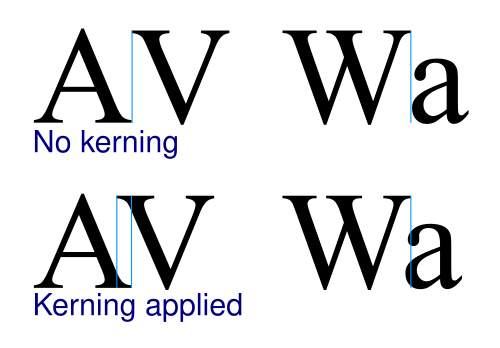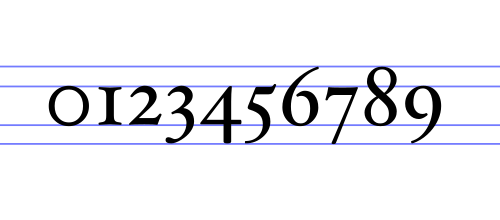
金属 活字組版において、フォント(アメリカ英語) またはファウント(イギリス英語) とは、書体の特定のサイズ、太さ、スタイルであり、全体的なデザインを共有するフォントのセットとして定義されます。たとえば、Bauer Bodoni書体 (図を参照) には、「 Roman」(または「regular」)、「bold」、および「italic 」のフォントが含まれており、それぞれさまざまなサイズがあります。
フォントのデジタル記述(コンピュータフォント)では、「フォント」と「書体」という用語はしばしば同じ意味で使用されます。[1]たとえば、コンピュータで使用する場合、各スタイルは個別のデジタルフォントファイルに保存されます。
従来のタイプセッティングとコンピューターの両方において、「フォント」という言葉は書体の配信メカニズムを指します。従来のタイプセッティングでは、フォントは金属または木製の活字から作られ、ページを構成するには複数のフォント、さらには複数の書体が必要になる場合があります。
綴りと語源
フォント(米国)またはファウント(英国では伝統的、いずれの場合も/ f ɒ n t /と発音)という単語は、中世フランス語の「鋳鉄」を意味する fonte に由来しています。[ 2 ]この用語は、活字鋳造所で金属活字を鋳造する工程を指します。綴りのfont は主に米国で使用されていますが、fount は歴史的にほとんどの英連邦諸国 で使用されていました。
金属タイプ
手作業による印刷 (活版印刷) 工場では、「フォント」という言葉は、ページ全体を植字するために使用される金属活字一式を指します。大文字と小文字は、手作業による植字の際に金属活字がどちらのケースに配置されていたかによってその名前が付けられます。つまり、大文字はより遠く、小文字はより近いということです。同じ区別は、大文字と小文字という用語でも表されます。
デジタル書体とは異なり、金属フォントには各文字の単一の定義は含まれませんが、よく使用される文字 (母音やピリオドなど) には、より多くの物理的なタイプピースが含まれます。新品で購入したフォントは、多くの場合 (たとえばローマ字の場合) 12pt 14A 34a として販売されており、これは、14 個の大文字の「A」と 34 個の小文字の「a」を含む 12ポイントフォントであることを意味します。
残りの文字は、その言語の文字の配分に適した量で提供される。ダッシュ、スペース、行の高さのスペーサーなど、植字に必要な金属活字の一部は、特定のフォントの一部ではなく、どのフォントでも使用できる汎用的な部分であった。[3]行間隔は、行間隔に使用されるストリップが鉛(他の部分に使用されているより硬い合金ではなく)で作られているため、今でも「リーディング」と呼ばれることが多い。このスペーシングストリップが鉛で作られているのは、鉛が従来の鍛造金属活字片(鉛、アンチモン、スズの一部)よりも柔らかい金属であり、印刷「チェイス」(つまり、すべての活字を一緒に保持するキャリア)に「固定」されたときに簡単に圧縮されるためである。
1880 年代から 1890 年代にかけて、「ホット リード」植字法が発明されました。これは、活字を 1 文字ずつ (モノタイプ技術の場合)、または活字の行全体を一度に (ライノタイプ技術の場合) 鋳造して植字する技術です。
特徴
機械的な意味での用語を使用する場合、文字の高さに加えて、フォントを区別する特性がいくつかありますが、それらは書体がサポートするスクリプトにも依存します。ヨーロッパのアルファベットスクリプト、つまりラテン文字、キリル文字、ギリシャ文字の場合、主な特性は、ウェイトと呼ばれるストロークの幅、スタイルまたは角度、および文字幅です。
レギュラーまたは標準フォントは、ボールドまたは細字、イタリックまたは斜体と区別するために、ローマン というラベルが付けられることがあります。デフォルトのレギュラー ケースのキーワードは、バリアントでは省略されることが多く、繰り返されることはありません。そうでない場合は、 Bulmer レギュラー イタリック、Bulmer ボールド レギュラー、さらにはBulmer レギュラー レギュラーになります。ローマンは、フォントの言語範囲を指すこともあり、「西ヨーロッパ」の省略形として機能します。
同じ作品の中で、読みやすさや強調の度合いを変えるために同じ書体の異なるフォントが使用される場合や、視覚的に興味をそそるようなデザインに使われる場合もあります。
重さ
特定のフォントにおける太さは、文字の高さに対する文字のアウトラインの太さです。
書体には、極細から極太、黒まで、さまざまな太さのフォントがあります。4 から 6 の太さは珍しくなく、12 種類もある書体もあります。オフィス、Web、非専門家向けの書体の多くには、連結された標準太さと太字の太さがあります。太字の太さが指定されていない場合、多くのレンダラー (ブラウザー、ワード プロセッサ、グラフィック プログラム、DTP プログラム) は、アウトラインをオフセットで 2 度レンダリングするか、斜めの角度でわずかにぼかすことで、太字フォントをサポートします。
基本の太さは書体によって異なります。つまり、あるフォントは別のフォントよりも太く見える場合があります。たとえば、ポスターで使用することを目的としたフォントはデフォルトで太字になっていることが多いですが、長いテキスト用のフォントはむしろ細字になっています。フォント名の太さの指定は、フォント内の実際の絶対的な線の太さやグリフの密度とは異なる場合があります。
さまざまなウェイトを体系化しようとした結果、1957 年にAdrian FrutigerがUnivers書体で初めて使用した数値分類が生まれました。数値は 35 Extra Light、45 Light、55 MediumまたはRegular、65 Bold、75 Extra Bold、85 Extra Bold、95 Ultra BoldまたはBlackです。これらの派生版には、「6 シリーズ」(イタリック体) (例: 46 Light Italicsなど)、「7 シリーズ」(コンデンス バージョン) (例: 57 Medium Condensedなど)、「8 シリーズ」(コンデンス イタリック体) (例: 68 Bold Condensed Italics ) などがあります。この簡潔な数値システムにより、フォントの特性を正確に判断しやすくなります。たとえば、「Helvetica 67」(HE67) は「Helvetica Bold Condensed」と翻訳されます。
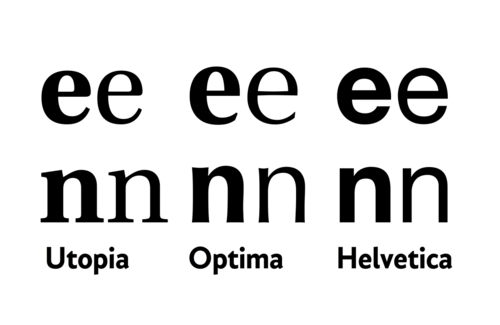
はモノライン デザインで、太字になるほどすべてのストロークの太さが増します。OptimaやUtopiaなどのモノ
ラインの少ないフォントでは、太いストロークの太さが増します。3つのデザインすべてにおいて、「n」の曲線は左側の縦線と結合するにつれて細くなります。
フォントの最初のアルゴリズム記述は、1986 年にDonald KnuthがMetafont記述言語とインタープリタで作成しました。
TrueTypeフォント形式では 100 から 900 までのスケールが導入されました。これは CSS や OpenType でも使用され、400が標準(ローマンまたはプレーン) になります。
Mozilla Developer Networkは、一般的なフォントの太さの名前に 次のような大まかなマッピング[4]を提供しています。
フォントのマッピングはフォントデザイナーによって異なります。良い例としては、Bigelow と Holmes の Go Go フォントファミリーがあります。このファミリーでは、「フォントには CSS 数値ウェイトが 400、500、600 あります。CSS では「太字」を 700 ウェイト、600 を Semibold または Demibold として指定していますが、Go 数値ウェイトは実際のステムの太さの比率の進行と一致しています。Normal:Medium = 400:500、Normal:Bold = 400:600」。[5]
normal、regular、plain ( bookと呼ばれることもあります)という用語は、書体の標準太さのフォントに対して使用されます。両方が表示され、異なる場合、book は多くの場合、 regularよりも細字ですが、書体によっては太字になります。
コンピュータが登場する前は、各ウェイトを手動で描画する必要がありました。その結果、Gill SansやMonotype Grotesqueなどの古いマルチウェイト ファミリの多くは、ライトからエクストラ ボールドまでウェイトにかなりの違いがあります。1980 年代以降、トレンド、マルチプル マスター、またはその他のパラメータ化されたフォント デザインに沿ったポイントとして、自動化を使用してウェイトの範囲を構築することが一般的になっています。つまり、MyriadやTheSansなどの多くの最新のデジタル フォントは、1 つのウェイトから次のウェイトへのスムーズで連続的な移行を提供する幅広いウェイトの範囲で提供されていますが、一部のデジタル フォントは、大規模な手動修正で作成されています。
デジタルフォントデザインにより、より多くのバリエーションをより速く作成できるようになったため、プロのフォントデザインでは「グレード」の使用が一般的になっています。グレードとは、紙やインクの種類、または周囲の温度や湿度が異なる異なる地域での印刷を想定して、わずかに異なる太さのフォントを指します。[6] [7] [8]たとえば、本の用紙に印刷された細いデザインと、光沢のある雑誌用紙に印刷された太いデザインは、前者の場合、インクがより染み込んで広がるため、同じように見えることがあります。グレードは、すべてのグレードで同じ幅の文字で提供されるため、印刷材料が変わってもコピーフィットには影響しません。[9] [10]グレードは、より細かいディテールを持つセリフフォントでよく使用されます。
太字と非太字の文字の幅が同じフォントは「二重化」されます。
スタイル
スロープ
ヨーロッパの書体、特にローマ字の書体では、重要な単語を強調するために斜体が使用されます。これはイタリック体または斜体と呼ばれます。これらのデザインは通常、左から右に書く文字では右に傾いています。斜体スタイルはイタリック体と呼ばれることが多いですが、「真のイタリック体」スタイルとは異なります。
イタリック体は通常の書体よりも流れがあり、手書き風の筆記体に近く、合字がより一般的に使用されたり、スワッシュが追加されたりする可能性があります。まれに、タイポグラフィの書体に一致するカリグラフィの書体 (筆記体、スクリプト) が付随し、誇張されたイタリック体になることがあります。
多くのサンセリフ体と一部のセリフ体、特に均一な太さのストロークを持つ書体では、斜体フォントの文字は斜体になっているだけです。これは多くの場合、アルゴリズムによって行われ、外観は変更されません。このような斜体フォントは、小文字の形状が変わらないため、真の斜体ではありませんが、そのように販売されることがよくあります。フォントには通常、斜体と斜体の両方のスタイルは含まれません。デザイナーがどちらか一方を選択します。
- ^ 金属活字では、フォントのポイント サイズは、書体の文字が鋳造された金属本体の高さ(幅ではない) を表します。この書体は、ウィリアム アディソン ドウィギンズによる「ファルコン」デザインでしたが、結局は発行されませんでした。